Pada bulan ini juga terdapat sebuah produk google yang diberi nama "Google Noto Fonts". Ketika teks diterjemahkan oleh komputer, kadang-kadang karakter yang ditampilkan berbentuk kotak seperti 'tahu'. Kotak-kotak kecil itu menunjukkan perangkat komputer anda tidak memiliki font untuk menampilkan teks tersebut, disinilah peran Google Noto Font yaitu bertujuan untuk mendukung semua bahasa dengan tampilak yang lebih harmonious.
Alva Free Font
Font geometris minimalis untuk poster dan headline.
Cornerstone Font
Font yang sangat cocok digunakan untuk desain bertema sport atau urban(perkotaan)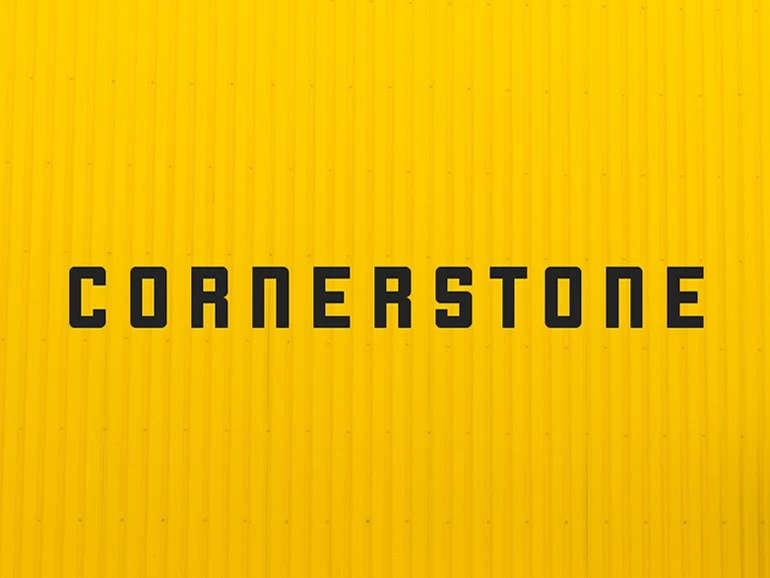
Devious Handmade Typeface
Font handmade yang simple dan lebih menonjoolkan kesan antik/elegan.
Google Noto Font
Adalah keluarga tipografi yang mendukung semua bahasa dengan tampilan yang lebih harmonious font ini memiliki berbagai style (multiple style) dan weight yang tersedia secara gratis semuanya.
Hane Free Font
Font vector gratis yang terinspirasi dari model arsitektur gedung perkotaan.
Humger Font
Font Grunge gratis yang bisa dipakai di desain kaos, gratis untuk penggunaan personal ataupun komersial.
Monophone Grunge Font
Font jenis fancy dengan vintage style yang cocok diaplikasikan sebagai header dan branding.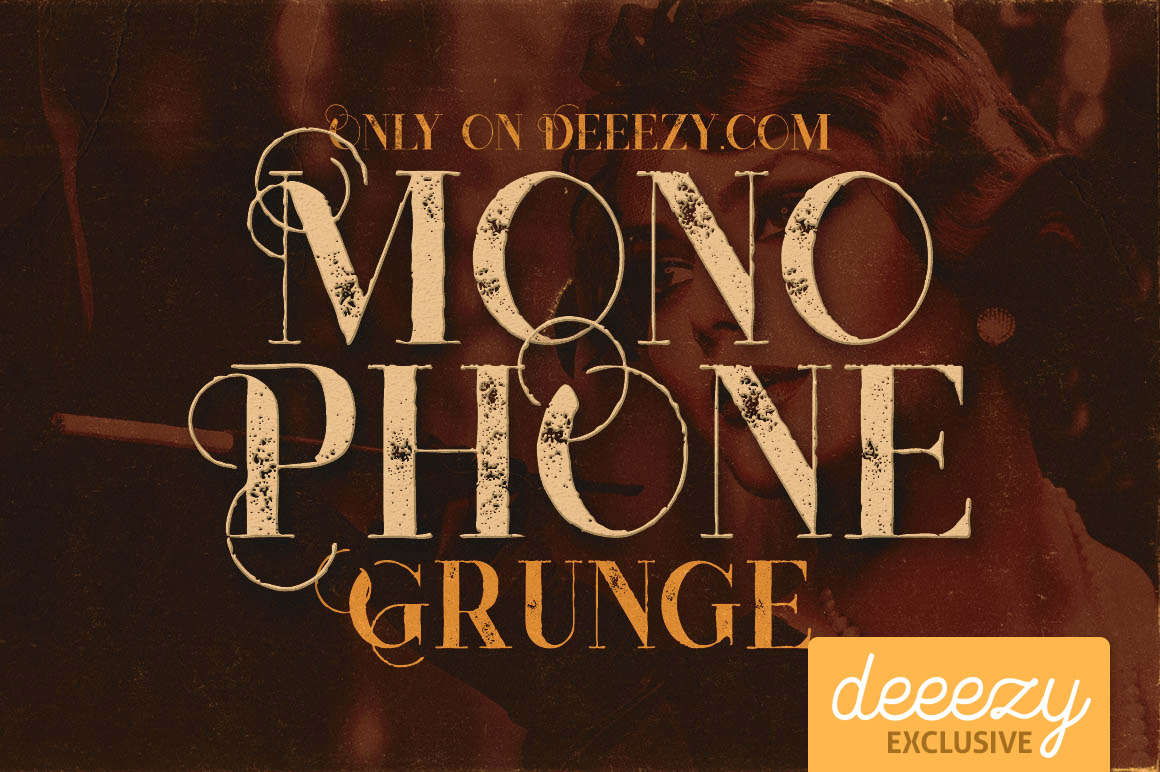
Noelan Caligraphy Typeface
Memiliki desain yang rapi dan modern, Noelan sangat cocok bagi anda yang senang membuat tipografi yang bisa diaplikasikan untuk kaos, poster atau lainnya dan pastinya gratis untuk personal dan komersial.
Nomes Typeface
Merupakan font gratis dengan perbedaan yang mencolok antara garis stroke yang tipis dan tebal, sangat cocok untuk poster, brosur dan banyak lagi.
Octanis Free Font
Modern font family lengkap yang sempurna untuk komposisi tipografi, headline dan logo. dalam font ini tersedia 8 style desain sans serif berbeda seperti light style, italic style dan lainnya.
The Woodlands Typeface
Adalah modern caligraphy font yang diciptakan untuk memberikan alterative font gratis yang tidak kalah bagus dengan font premium untuk membuat desain tipografi terlihat lebih menarik dan elegan, gratis untuk personal ataupun komersial.